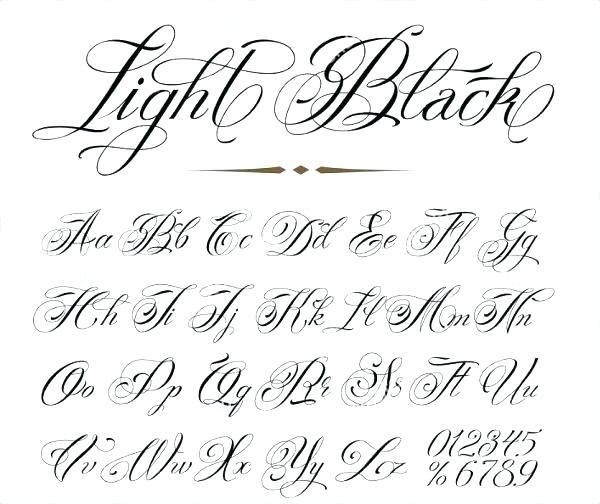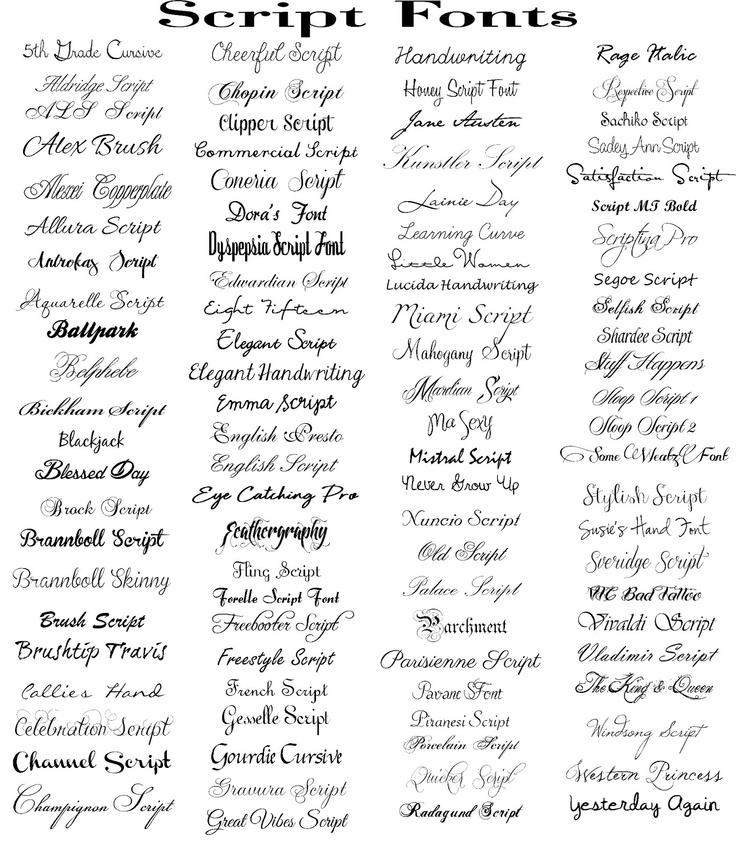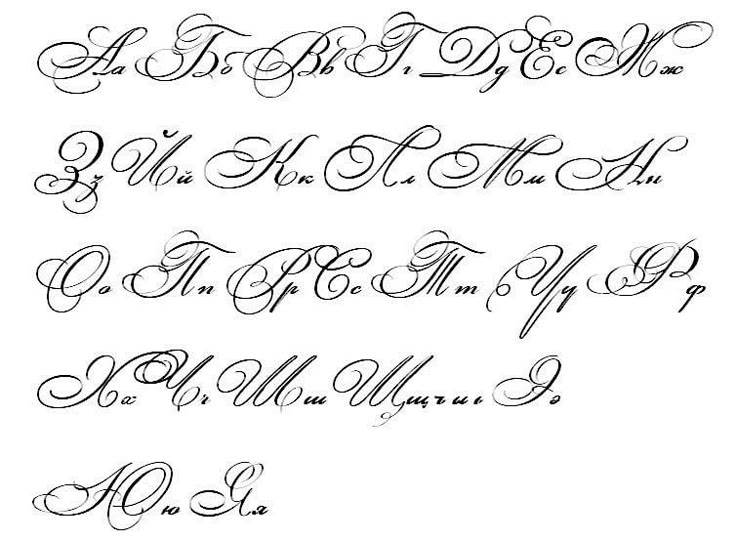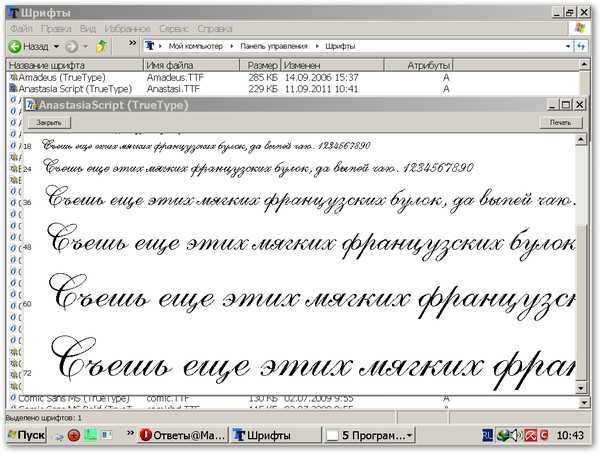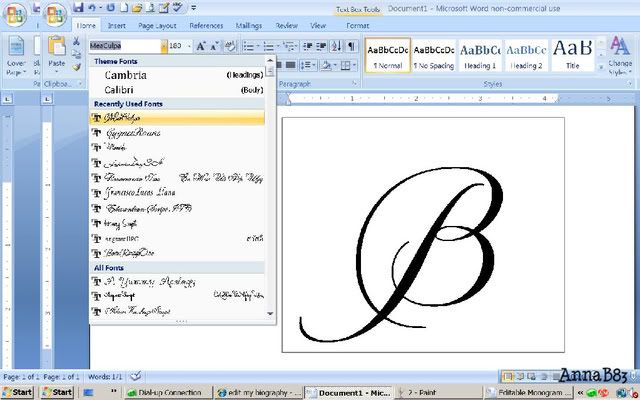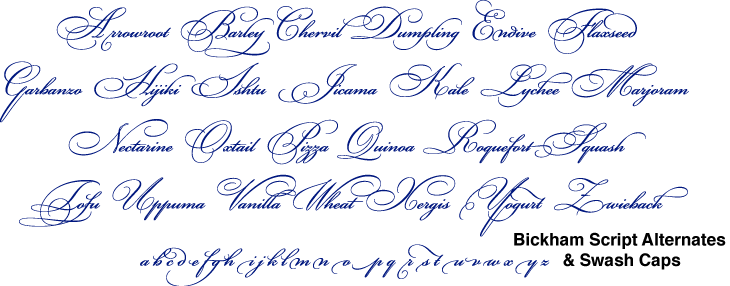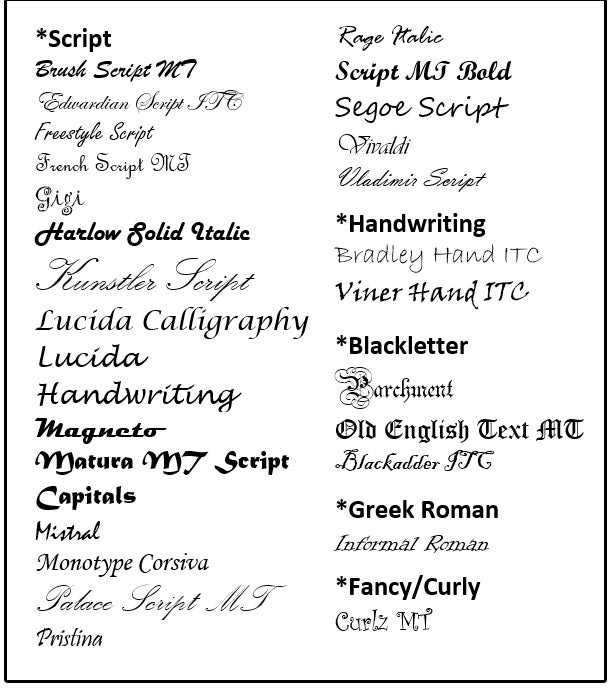
Красивый прописной шрифт в ворде: Как сделать рукописный шрифт в Ворде
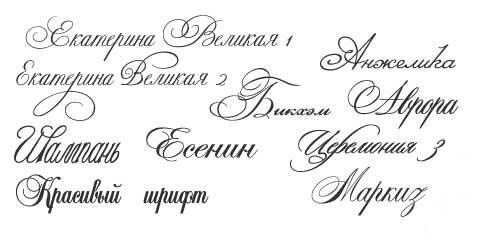
-
Стиль шрифта при написании реферата – Times New Roman.
-
Шрифт для реферата по ГОСТу – 14 пт.
-
Стандартный цвет букв – черный. -
В основном тексте документа не используется подчеркивание, курсив и полужирное выделение.
Важно! Следует внимательно изучить методические рекомендации вуза по оформлению исследовательских проектов. Исключением из общих правил может стать оформление формул и примеров внутри документа
Что можно писать прописным шрифтом
Каждый с детства знает, что любое новое предложение пишется с прописной буквы. Но при написании реферата необходимо знать об исключениях. В исследовательских работах есть слова и предложения, которые печатаются только заглавными буквами.
С 5 шрифтами, прописными буквами, цифрами и пунктуацией, Avocado – выбор для профессионалов. Он идеально подходит для упаковки продуктов, заголовков журналов и многого другого.
Reckonen — лучший шрифт из нашей подборки шрифтов с заглавными буквами, когда речь идет о современном промышленном дизайне. Шрифт предоставляется бесплатно.
Вена | Современный шрифт с засечками
Компания Big Cat Creative разработала один из самых элегантных шрифтов с засечками на рынке — Vienna.